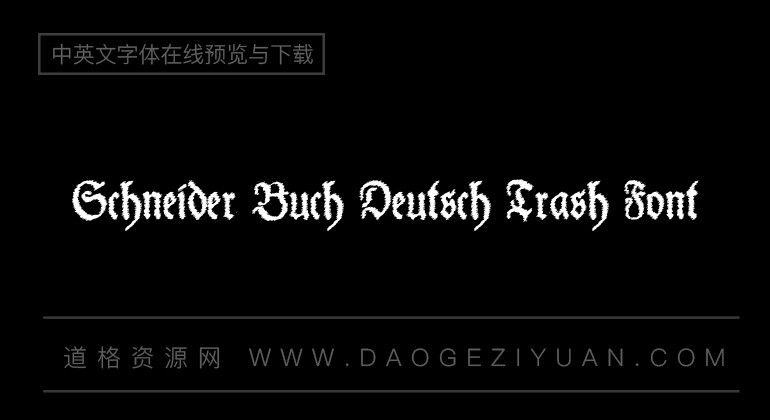
Schneider Buch Deutsch Trash Font 是一种德文垃圾邮件字体,具有独特的粗糙和不规则的外观。它模仿了传统的老旧德文印刷字体风格,但是在字母的形状和排列上故意加入了一些不规则和失真的元素,使得整个字体看起来有一种垃圾般的质感。 Schneider Buch Deutsch Trash Font 给人一种非常另类的感觉,适合用于一些需要突出个性和不拘一格的设计场合,如音乐海报、电影海报、街头时尚、杂志封面等。此外,由于其独特的外观,Schneider Buch Deutsch Trash Font 还被一些时尚品牌和年轻人群喜欢,用于他们的品牌标识、广告和宣传等。内容介绍
Schneider Buch Deutsch Trash Font是一款非常不错的手写艺术字体,具有很好的视觉感,适合于文化类的宣传设计、商业类品牌的广告和产品包装设计以及个性化文字排版等较多场景。